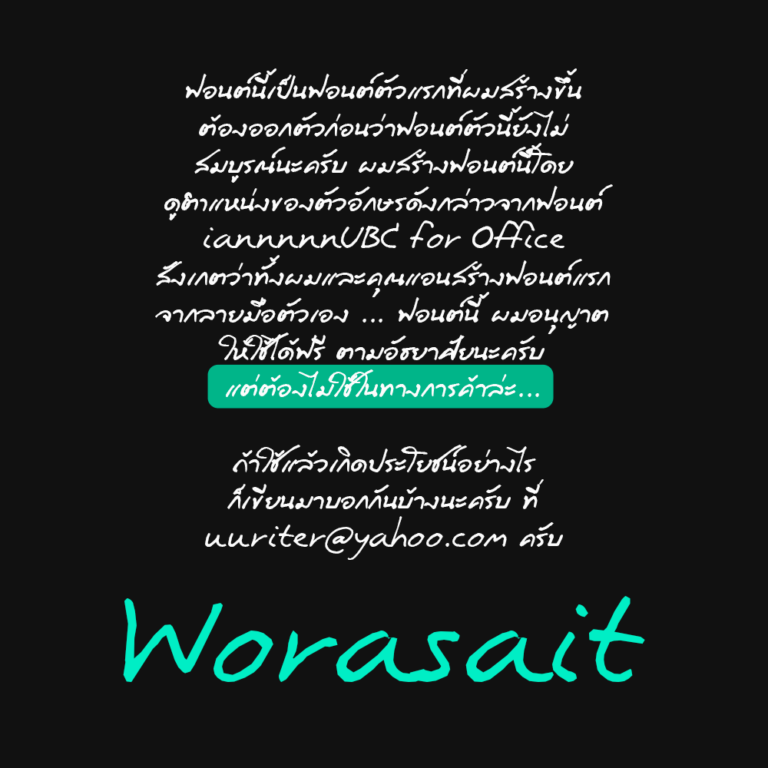
ฟอนต์วรเศรษฐ
” ฟอนต์นี้เป็นฟอนต์ตัวแรกที่ผมสร้างขึ้น ต้องออกตัวก่อนว่าฟอนต์ตัวนี้ยังไม่สมบูรณ์นะครับ ผมสร้างฟอนต์นี้โดยดูตำแหน่งของตัวอักษรดังกล่าวจากฟอนต์ iannnnnUBC for Office สังเกตว่าทั้งผมและคุณแอนสร้างฟอนต์แรก จากลายมือตัวเอง … ฟอนต์นี้ ผมอนุญาตให้ใช้ได้ฟรี ตามอัธยาศัยนะครับ แต่ต้องไม่ใช้ในทางการค้าล่ะ … ถ้าใช้แล้วเกิดประโยชน์อย่างไร ก็เขียนมาบอกกันบ้างนะครับ ที่ uuriter@yahoo.com ครับ”